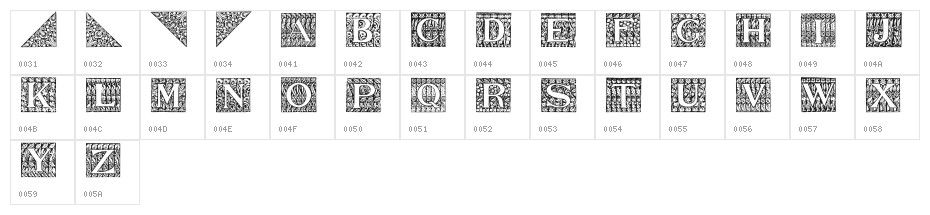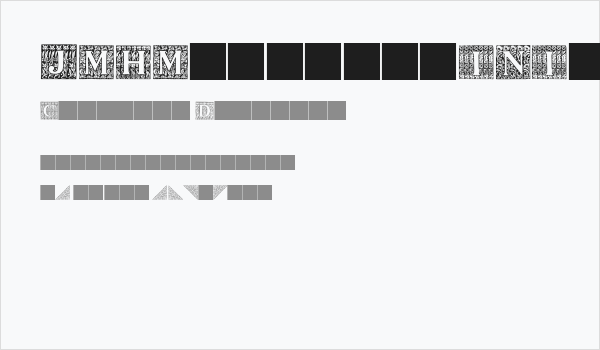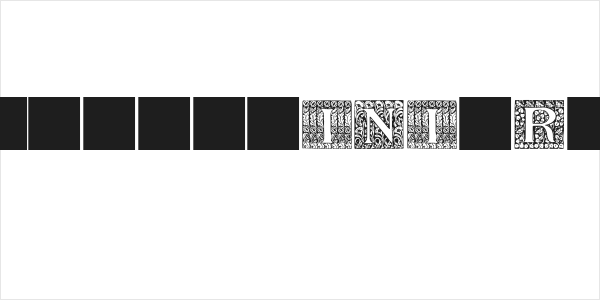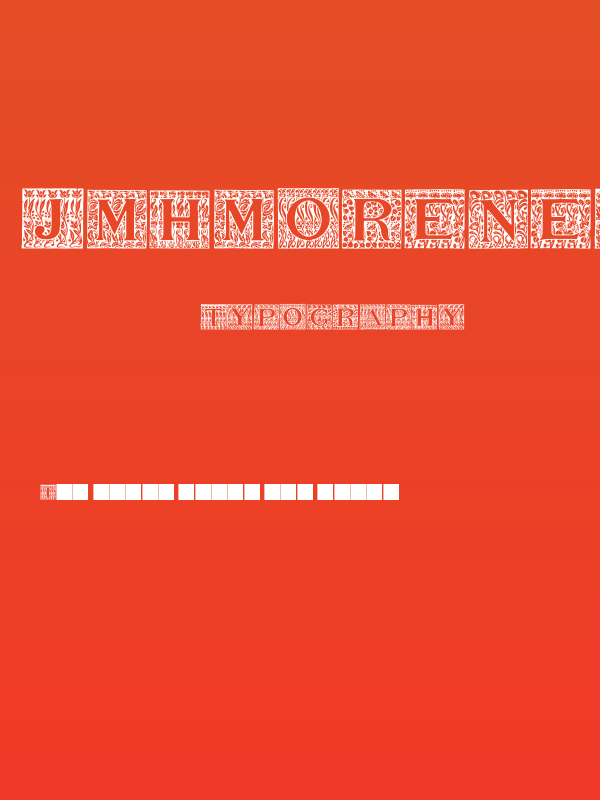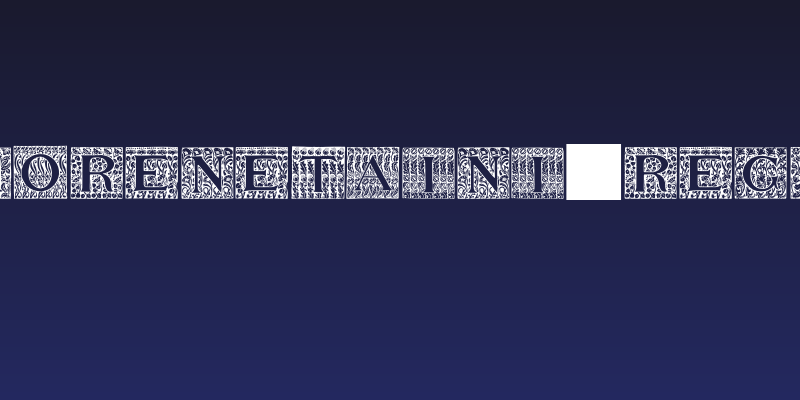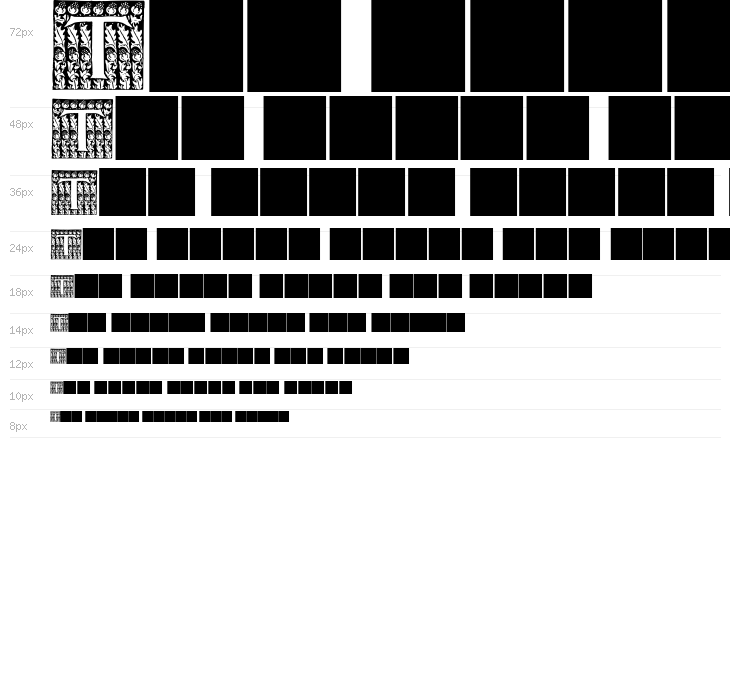
JMHMorenetaINI-Regular Font
| Proyectos propuestos | Ideal for artistic projects, book covers, posters, and invitations that require a decorative and sophisticated touch. |